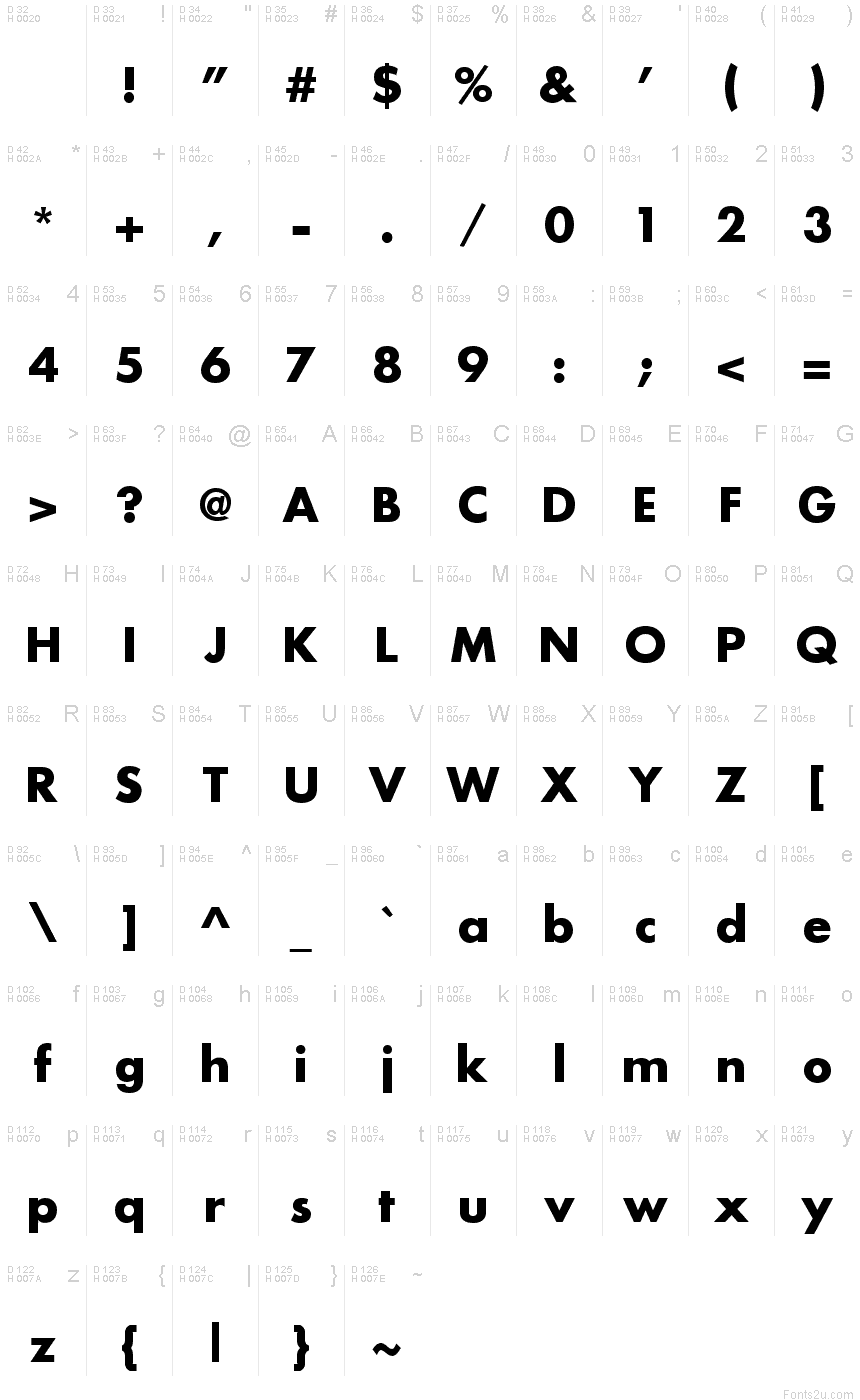
Intrepid Bold je bezplatné, výrazně tučné bezpatkové písmo. Masivní, blokové tvary s pevnými svislicemi a hladkými, zaoblenými křivkami mu dodávají silný, a přitom přátelský charakter, jako by barva byla otisknuta hluboko do papíru. Díky těsnějšímu rozestupu působí slova kompaktně a úderně, takže nadpisy fungují okamžitě i bez zbytečných efektů. V rámci širší rodiny Intrepid je tento řez spolehlivým základem všude tam, kde potřebujete, aby sdělení vyniklo a bylo čitelné i z dálky.
S Intrepid Bold získáte výrazný rytmus, který skvěle vynikne na plakátech, bannerech, grafice pro sociální sítě, obalech produktů, letácích na akce i v moderních logotypu. Tvary zůstávají jednoduché a otevřené, což zajišťuje, že je toto bezplatné písmo snadno čitelné i při menší velikosti nadpisů na webu a mobilních zařízeních. Zkuste kombinovat Intrepid Bold s lehkým geometrickým bezpatkovým písmem nebo úhledným patkovým písmem pro hlavní text, aby tento řez nesl hlavní sdělení, zatímco druhý typ písma obstará delší text.